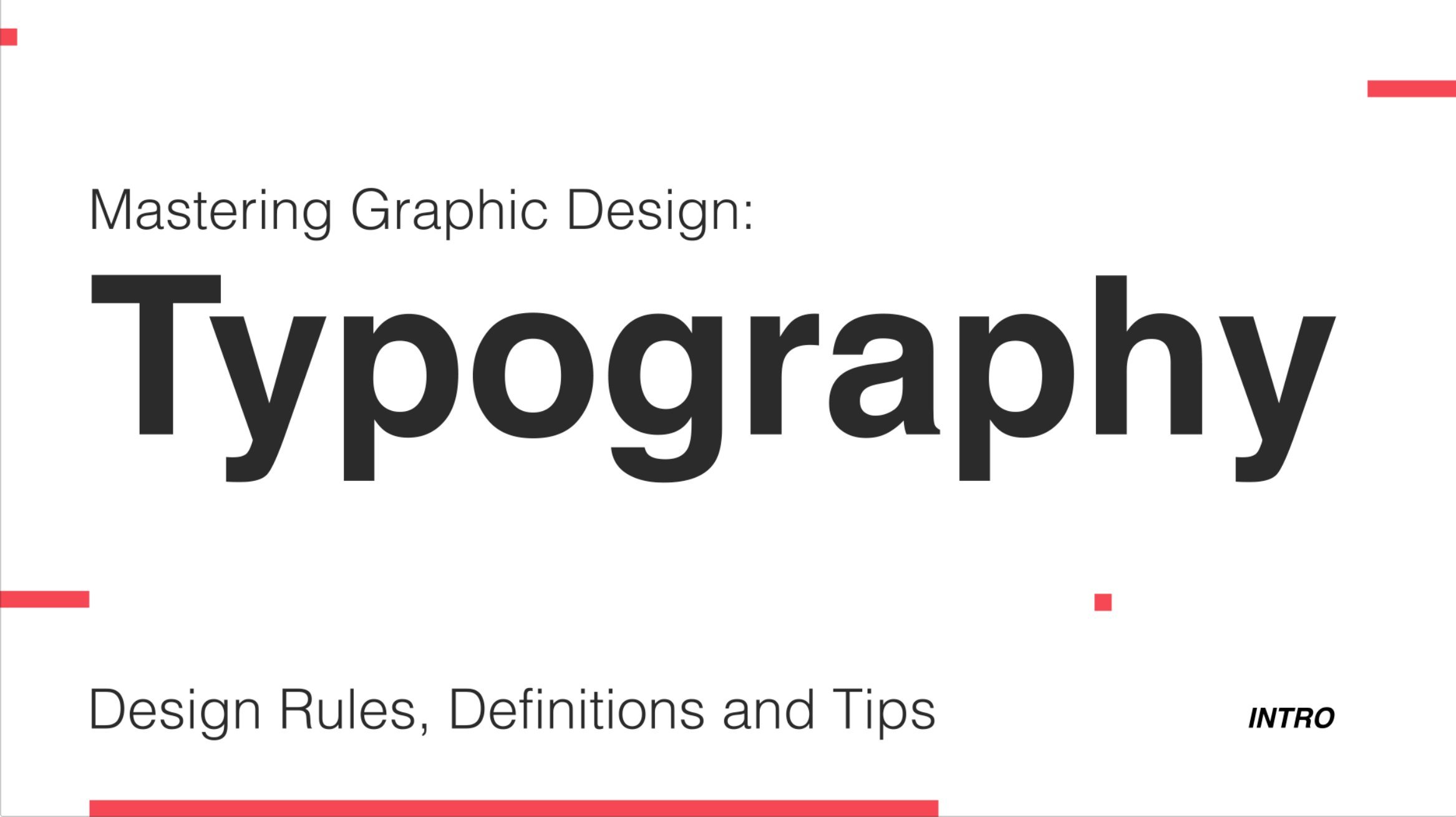
Typografie: 8 Regeln zur sofortigen Verbesserung deines Typography:
Verfolgung und Kerning
Führen
Rags
Witwen und Waisen
Links ausrichten
Schriftgewicht
Schriftgröße
Raster und Layout
Eine Schrift
Weißraum
Nähe
Die Regeln brechen
Das Projekt
Über diesen Kurs
Love aber fehlt an Typografie Feuerkraft?
Benötigen Sie eine Auffrischung der Typischen Regeln?
Ganz neu dabei?
Wenn einer dieser dir nach dir klingt - das ist der richtige Ort für dich! Ein umfassender Kurs, der dir die alte Weisheit verleiht, ein Typografie Großmeister zu werden!
Was du lernen wirst:
Wir decken alle wichtigen typography und deren Definitionen sowie goldene Regeln und Designtipps ab.
Was du machen wirst:
Wenn du all deine neuen Fähigkeiten in die Praxis setzst, erstellen wir am Ende des Kurses ein Plakatdesign. Wir werden das Gleichgewicht von Text und Bildern üben und wie du sie anwenden kannst, um sich gegenseitig zu ergänzen.
1. Kursinhalte: Hallo und willkommen zu meinem Video über Typografie. In dieser Klasse werden wir mit dem Erlernen der wichtigsten typografischen Begriffe und deren Definitionen beginnen. Und wir gehen auf acht, typografische Rose, um sowohl Ihre Typografie als auch Ihre Design-Fähigkeiten auf die nächste Stufe zu bringen. Beenden Sie die Klasse mit einem Projekt, in dem Sie alle Bits, die Sie während des Videos gelernt haben, in die Praxis umsetzen können . Beginnen wir also mit der Definition der Topographie. Topographie ist die Kunst, geschriebene Sprache lesbar, lesbar und ansprechend zu machen. Was ist der Unterschied zwischen lesbar und lesbar? Ich höre Sie fragen, naja, lustig genug, ist die Lesbarkeit definiert als klar genug, um zu lesen. Hören Sie mich auf. Zum Beispiel ist der Typ auf der linken Seite viel lesbarer als der Typ auf der rechten Seite. Und wie für lesbar, wo alle diese Absätze lesbar sind, lesen sie nicht in der beabsichtigten Weise. Durch die Organisation des Textes sind sie viel lesbarer. 2. Tracking und Kerning: Durch das Nachverfolgen in Kerning bezieht sich auf den Abstand zwischen Zeichen. Aber es gibt einige Unterschiede, die ich erklären werde. Kerning ist speziell der Abstand zwischen einem Paar von Zeichen. Zum Beispiel haben diese a und V keine Kerning. Und Sie können sehen, dass die Oberseite der VA mit der Basis des a ausgerichtet ist. Aber wenn Sie Kerning hinzufügen, überlappt die Oberseite der VA nun die Basis des a. Und mit Kerning können Sie Zeichen entweder weiter auseinander schieben oder sie näher beieinander. Zum Beispiel, hier ist Welle ohne Kerning und dann Welle mit Kerning. Es gibt einen ziemlich großen Unterschied. Also wurde Kerning zwischen dem W und dem a, dem a und dem v und dem V und dem a hinzugefügt dem v und dem V , wobei die Kerning angepasst und speziell für ein Paar von Zeichen geeignet ist. Trucking ist ein konstanter Abstand, der zwischen allen Zeichen in einem größeren Textblock festgelegt ist. Oft wird Tracking verwendet, anstatt in größeren Textblöcken zu koppeln, da es zu lange dauern würde, jedes Paar von Zeichen einzeln zu zählen. Um den Unterschied zwischen Tracking und Kerning iRemember Token zu Zeichen zu erinnern, sind freundlich. 3. Führen: Lesen ist die Größe des Speicherplatzes von der Basislinie zu der Basislinie. Die Kreditvergabe ist ein wesentlicher Bestandteil der Topographie, da sie sich direkt auf die Lesbarkeit Ihrer Arbeit auswirkt. Zum Beispiel ist dieser Absatz zusammengefügt und es gibt nicht viel Ledi, aber nur ein wenig Kreditvergabe erhöht die Lesbarkeit enorm. Es gibt tatsächlich eine einfache Formel, die ich jedes Mal für die Berechnung meiner Hochzeit verwende. Es ist Schriftgröße plus Ihre Schriftgröße geteilt durch vier. Und es funktioniert wie Magie. Du fühlst dich wie ein Mathe-Genie Washer da drin. 4. Rags: Prags des unebenen Zeitalters des Textes. Zum Beispiel ist in diesem ersten Absatz der Lappen auf der rechten Seite glatt und gestreift. In diesem zweiten Absatz ist der Lappen jedoch Jaggard, sein Zickzack ist einfach schrecklich. Wenn Sie Ihren Lappen richtig machen, können Sie Ihre Lesbarkeit und die Attraktivität Ihres Textes erhöhen. Und es gibt nichts Schlimmeres als Designer, das bemerkt ein schlechtes Rack. Dies sind die drei wichtigsten Möglichkeiten, die ich meine eigenen korrigieren. Zuallererst verwende ich Bindestriche. Ich kann das Wort aufteilen, und das wird das Problem oft beheben. Zweitens, ich werde meine Spalte es anpassen. Und drittens kann ich meinen Text anpassen, mein Exemplar, um ein kürzeres oder längeres Wort zu enthalten, kann den Lappen ansprechender aussehen lassen. 5. Witwen und Waschen: Ja, ich mach keine Witze. Witwen und Waisen sind typografische Begriffe. Eine Witwe ist eine sehr kurze Zeile in der letzten Zeile eines Absatzes. Und eine Waise ist eine sehr kurze Zeile in der ersten Zeile einer neuen Spalte oder Seite. Witwen und Waisen oder ein Problem in der Typografie weil sie die Lesbarkeit eines Textes stören. In diesem Artikel gibt es einige Beispiele für Witwen und Waisen. Die sehr kurze Zeile am Ende des ersten Absatzes ist eine Witwe. Und das einzelne Wort in der zweiten Spalte ist ein, oft, es sieht ziemlich einsam aus, nicht wahr? Diese Worte sehen unzusammenhängend aus dem Rest ihres Textes ist, wenn es einen nachträglichen Gedanken. Korrektur Ihrer Witwen und Waisen ist der gleiche Vorgang wie die Korrektur Ihrer Lumpen. Sie können eine gestische Spaltenbreite mit Silbentrennung versehen, in der Sie Ihre Kopie anpassen können. 6. Left: Dies ist ein einfacher Tipp, aber einer der effektivsten. Es ist kein Zufall, dass alle Zeitungen, Bücher und Website-Artikel mit linksbündigem Text geschrieben werden. In der westlichen Welt lesen wir von oben nach unten, von links nach rechts. Es ist Teil unserer Natur geworden, wenn Sie eine Zeile gelesen haben , um zur linken Seite des Absatzes zurückzukehren. Mit Text nach rechts ausrichten. Wir kehrten zur linken Seite des Absatzes zurück und unsere Augen haben ein unbewusstes Rührei, um zu versuchen, das nächste Wort zu finden, um die Lesung weiterzuführen. Letztendlich erhöht linksbündig die Lesbarkeit unserer Topographie. Und das ist der Schlüssel, um unsere Botschaft an den Leser weiterzuleiten. 7. Schriftgewicht: Wenn Sie verschiedene Schriftgewichtigkeit verwenden, sollten Sie immer versuchen, warten zu lassen. Zum Beispiel, mit Licht und Fett als warten Paarung. Sie sollten dies tun, weil es Kontrast hinzufügt, was ein Schlüsselelement im Design ist. Es führt auch die Hierarchie ein. Dies ist die Art und Weise, in der der Betrachter um die Seite geführt wird. Wenn beispielsweise Text derselben Größe vorhanden ist, liest der Betrachter am ehesten vorab fett formatierten Text. Es ist wie ein Gegenstück. Überspringen des Gewichts zeigt auch Ihre Absicht. Wenn Sie fett und normal oder unregelmäßig und leicht sind, sind diese sehr ähnlich und manchmal kann der Leser sie als Fehler sehen. Wenn Sie erwarten und fett und hellen Text verwenden, dann ist der Unterschied viel deutlicher. Und es zeigt Absicht. 8. Schriftgröße: Bei Verwendung unterschiedlicher Schriftgrößen verwenden wir runde Zahlen, wenn Sie nach oben oder unten skalieren. Zum Beispiel ist dieser Text 82, w, das ist 164. Und wieder, 328. Ähnlich wie unsere Schriftlichter tun wir dies für die Kontrasthierarchie. Und um die Absicht zu zeigen. Wo sich diese beiden Schriftgrößen nur geringfügig unterscheiden, könnte sie vom Leser als Fehler interpretiert werden. Durch das Festhalten an runden Zahlen, Verdoppelung, Verdreifachung oder Vervierfachung, macht es die Entwürfe klar. 9. Raster und Layout: Als ich das erste Mal über das Gittersystem und die Konstruktionsraster im Allgemeinen erfuhr, wurde ich weggeblasen. Es war wie eine Formel für ein perfektes Layout jedes Mal. Hier ist ein Beispiel dafür, was die Verwendung von Grid für Ihr Design tun kann. Nehmen Sie dieses Textmodell einfach, indem Sie den gleichen Inhalt in ein Raster einfügen. Es wird organisiert. Es ist leicht für das Auge, und es verbessert sicherlich die Lesbarkeit. Ein ähnliches Konzept wie das Rastersystem besteht darin, Ihren Inhalt an der Achse auszurichten. Zum Beispiel. Dies sind meine Titelfolien, die ich für diese Videos erstellt habe. Sie können sehen, dass mehrere Elemente auf die eine oder andere Weise ausgerichtet sind. Dies trägt dazu bei, einen Gesamteffekt aller Elemente zu erzielen , die als Teil des Designs zusammenarbeiten. Sobald Sie diese Videos fertig sind, auf jeden Fall, schauen Sie sich Designraster an, weil es die Art und Weise verändert hat , wie ich über Layout und Präsentation meiner Arbeit denke. 10. Eine Schrift: Dies ist ein weiterer einfacher Tipp, aber definitiv nicht einen zu übersehen. Verwenden Sie eine Schriftart. Eine Schriftart erhöht die Lesbarkeit des Designs, Lesbarkeit und die Konsistenz. Font Paarungen, Mischen von zwei Fonds, die sich gegenseitig ergänzen, kann effektiv sein, wenn gut gemacht. Aber um zu beginnen, empfehle ich, eine Schriftart zu beherrschen. 11. Weißraum: Leerraum oder negativer Raum ist der Teil eines Versuchsplans, der leer gelassen wird. Es hilft, grafische Elemente zu trennen. Bei effektiver Nutzung kann der Leerraum wichtige Aspekte Ihres Designs hervorheben. Es kann die Lesbarkeit und die Attraktivität erhöhen. Whitespace ist ein visueller Atemraum und erleichtert es dem Betrachter, Informationen zu verdauen. Hier ist ein Beispiel für Leerzeichen, die gut verwendet werden. 12. Nähe: Nähe zeigt Beziehung an. Dies bedeutet, dass zwei Elemente, die nahe beieinander liegen, als verwandt betrachtet werden. Zum Beispiel sind hier zwei Blöcke von Kreisen, die durch Farbe getrennt sind. Und hier sind die gleichen zwei Blöcke mit ein paar Kreisen umgeschaltet. Wir gruppieren nun durch die Position oder die Nähe statt die Farbe. Ein weiteres sehr häufiges Beispiel dafür ist in den Google-Suchergebnissen. Wir wissen, welche Informationen sich auf welche Website beziehen, denn wenn effektiv, Gruppierung. 13. Die Regeln brechen: All diese Tipps und Tricks sind gute Faustregeln und wer dazu beigetragen hat, lesbare und ansprechende Topografie zu schaffen . Aber Sie hätten gehört, dass die Sprichregeln gebrochen werden, und dies gilt für Typografie Zwei, indem Sie einen Standardsatz von Zeilen brechen, können Sie Ihnen helfen, Design heben sich vom Rest ab. Hier sind einige Beispiele für den Regelbruch in der Topographie. Sobald Sie zuerst anfangen, die Straßen zu meistern und sie zu brechen, werden Sie sich in einem Zyklus zwischen den beiden finden, indem Sie Rose verwenden , Regeln brechen, Regeln verwenden, und so weiter und so weiter. 14. DAS PROJEKT: Bevor wir also direkt in das Projekt eintauchen, lassen Sie uns einfach zusammenfassen, was wir heute gelernt haben. Also begannen wir, indem wir Tracking und Kerning betrachteten. Wir schauten uns an, Lumpen, Witwen und Waisen zu lassen. Dann gingen wir zu den goldenen Regeln der Topographie, wie Linksausrichtung, Schriftgewicht, Schriftgröße, Gitter und Layouts. Und wir haben uns auch die Verwendung einer Schriftart, die Verwendung von Leerzeichen, Nähe und schließlich die Regeln gebrochen. Und das ist viel in knapp 15 Minuten. Danke, dass du bei mir bleibst, aber wir sind noch nicht fertig. Nächstes Mal für das Projekt, in den Projektfeinden unten, habe ich einige meiner eigenen Fotos und einige Beispieltexte hinzugefügt. Fühlen Sie sich frei, diese oder einige Ihrer eigenen zu verwenden. Versuchen Sie, einige typografische Layouts zu erstellen, Text und Bilder zu mischen, und seien Sie geduldig. Es kann ein paar Versuche dauern, etwas zu bekommen, mit dem du glücklich bist. Hier ist etwas, das ich zusammengestellt habe, wenn dies alle Elemente betrachtet werden, die wir heute durchgemacht haben. Und wenn Sie diese coole Grafik verwenden wollen, die ich aus Ihrer Komfortzone gemacht habe und fühlen Sie sich frei. Sie können das auch mit den Bildern im Beispieltext herunterladen. Fühlen Sie sich frei, von meinem eigenen Design zu arbeiten, oder Sie können sich etwas völlig Neues einfallen lassen. Denken Sie daran, Patrick-Klassen zu sehen, wenn Sie stecken bleiben oder wenn etwas nicht richtig aussieht und definitiv Ihre Projekte mit mir teilen, würde ich gerne sagen, was jeder einfällt. Vielen Dank für Ihr Kommen und ich wünsche Ihnen alles Gute auf Ihrer Reise , um ein Topografie Großmeister zu werden.